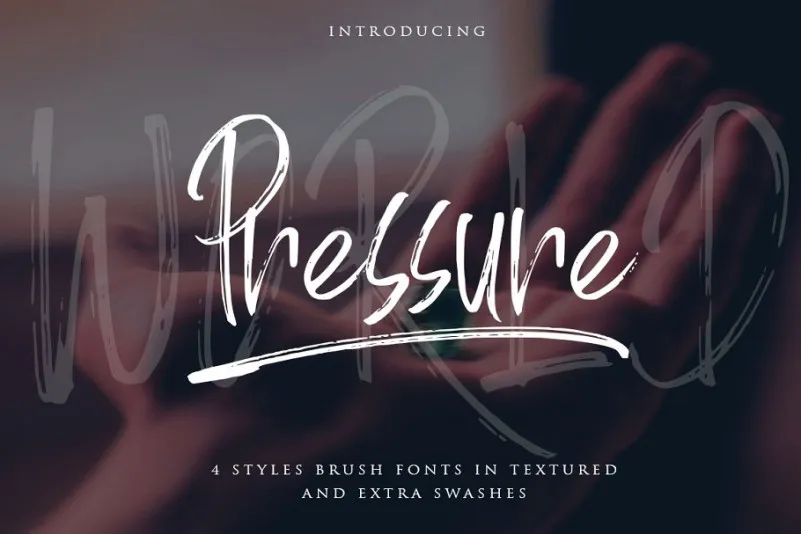
World Pressure Brush Font – Download Grátis
Esta página apresenta a World Pressure Font Brush Script, uma opção moderna e vibrante para designers de fãtua. Inspirada no estilo de rua, esta font traz um toque único e atemporal que se destaca por sua facilidade em criar mensagens dinâmicas e impactantes. Desenvolvida pelo designer 0001themes, a World Pressure Font é perfeita para diversas aplicações, desde projetos de marca até designs de mobiliário e embalagens de produtos. Seja como um overlay texturizado sobre qualquer imagem de fundo ou simplesmente adicionado à sua identidade visual, esta font oferece uma personalização única que torna suas ideias mais memoráveis. Com seu estilo autêntico e seus traços rápidos, a World Pressure Font é certamente a escolha perfeita para aqueles que buscam uma fonte de escrita livre que transmita a essência da sua mensagem. Este conjunto gratuito de fãtua vem com um toque único que se destaca entre os demais, tornando-o o ideal para qualquer projeto criativo em busca de um visual vívido e autêntico.